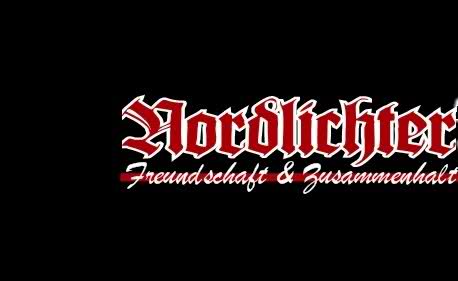
Die Basis ist auf jeden Fall die Wilhelm Klingspor.
Kräftig in die Breite gezogen, zusätzlich elektronisch fetter gemacht und dann noch eine Konturlinie drumrum. Lediglich das d weicht etwas ab.
Die Schreibschrift drunter ist eine dünner gemachte BrushScript.